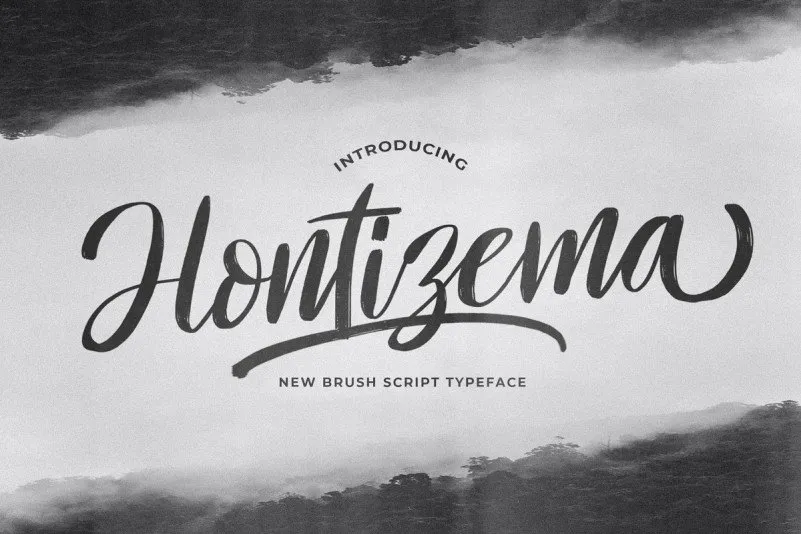
Hontizema Brush Font – Fonte Grátis
Hontizema Brush Font
A Hontizema Brush Font é uma elegante tipografia feita para designers visionários que buscam dar vida a seus projetos criativos. Ela foi desenvolvida pela StringLabs e incorpora características suaves e equilibradas, tornando-a perfeita para um vasto leque de designs. A fonte faz vibrar os mais inusitados conceitos, oferecendo uma textura única que se assemelha ao traçado manual de uma caneta-pipoca. Inclua a Hontizema Brush Font em seu trabalho e observe como ela transforma suas ideias em realidade, conferindo um toque único aos seus projetos. Ideal para designers que buscam expressar sua criatividade de maneira única e autêntica.